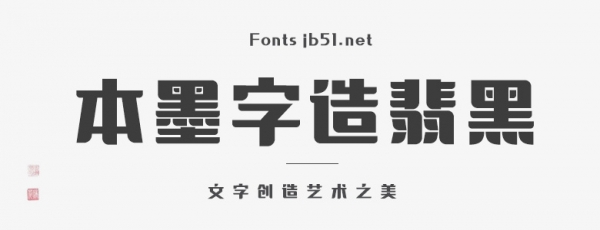
本墨字造翡黑是一款非常個(gè)性的黑體藝術(shù)字體,字型橫平豎直,修飾得宜,恰到好處,整體規(guī)范而不失特色。具有很好的視覺感,適合于文化類的宣傳設(shè)計(jì)、商業(yè)類品牌的廣告和產(chǎn)品包裝設(shè)計(jì)以及個(gè)性化文字排版等較多場(chǎng)景。